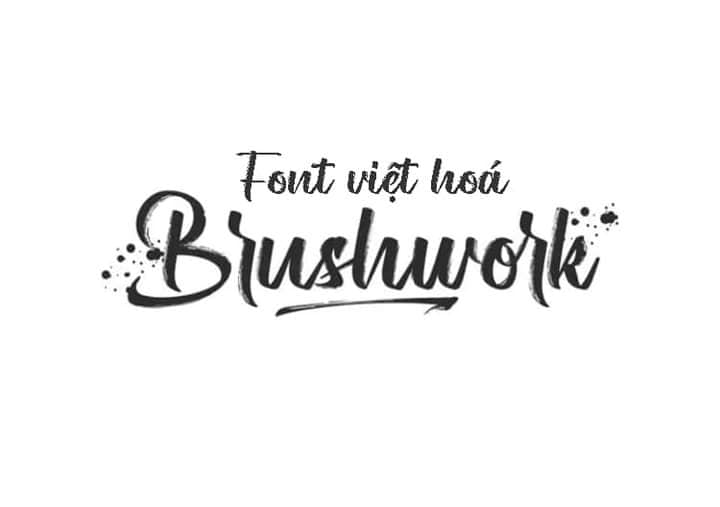
Font việt hoá MJ Brushwork – Brush – Sự lựa chọn hoàn hảo cho thiết kế năng động
Giới thiệu về Font việt hoá MJ Brushwork – Brush
Trong thế giới thiết kế đồ họa hiện đại, việc tìm kiếm một bộ Font Chữ mang phong cách nghệ thuật phóng khoáng luôn là ưu tiên hàng đầu của các bạn trẻ. Font việt hoá MJ Brushwork – Brush nổi bật như một tác phẩm hội họa với những đường nét cọ vẽ thủ công đầy mạnh mẽ và cá tính. Đây là phiên bản đã được tối ưu hóa bảng mã để các bạn học sinh và giáo viên có thể dễ dàng sử dụng trong các bài thuyết trình hay làm báo tường. Bộ font này tái hiện chân thực cảm giác mực in trên giấy, tạo nên sức hút thị giác đặc biệt cho mọi dự án sáng tạo.
Những đặc điểm nổi bật của MJ Brushwork – Brush
Phong cách thiết kế thủ công ấn tượng
Font việt hoá MJ Brushwork – Brush sở hữu những đường nét thô mộc nhưng không kém phần uyển chuyển. Mỗi ký tự đều được chăm chút kỹ lưỡng để giữ nguyên vẻ tự nhiên của nét cọ khô, mang lại chiều sâu và sự sống động cho văn bản. Đây là công cụ đắc lực để thiết kế tiêu đề sách, bìa vở hay các ấn phẩm truyền thông học đường.
Khả năng ứng dụng đa dạng và linh hoạt
Dù bạn đang thiết kế logo cá nhân hay trang trí poster cho câu lạc bộ, Font việt hoá MJ Brushwork – Brush đều đáp ứng tốt nhờ tính linh hoạt cao. Bộ font này giúp các bạn học sinh thể hiện được cái tôi nghệ thuật và sự phá cách trong từng sản phẩm. Đặc biệt, font đã được việt hoá đầy đủ dấu câu, giúp quá trình soạn thảo tiếng Việt trở nên mượt mà và không xảy ra lỗi hiển thị.
Kết luận về trải nghiệm sử dụng font